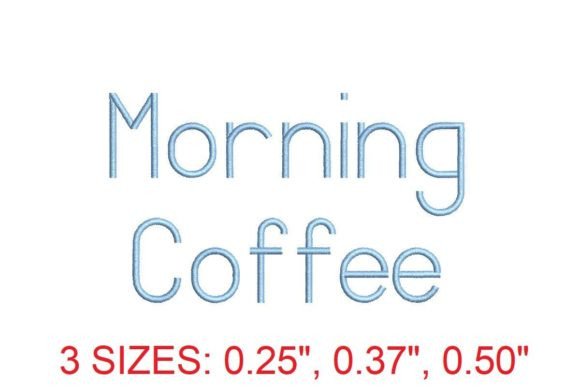
Morning Coffee Embroidery Font
Die richtigen Designelemente zu finden, kann eine Herausforderung sein, aber Morning Coffee Embroidery Font bietet eine außergewöhnliche Sammlung, die Ihre Arbeit sofort aufwertet.
Egal, ob Sie POD-Produkte (Print on Demand), Hochzeitseinladungen oder Social-Media-Grafiken erstellen, Morning Coffee Embroidery Font ist die ideale Wahl.
Experten-Tipp: Kombinieren Sie diese Elemente mit ergänzenden Schriftarten, um einzigartige, auffällige Designs zu kreieren.